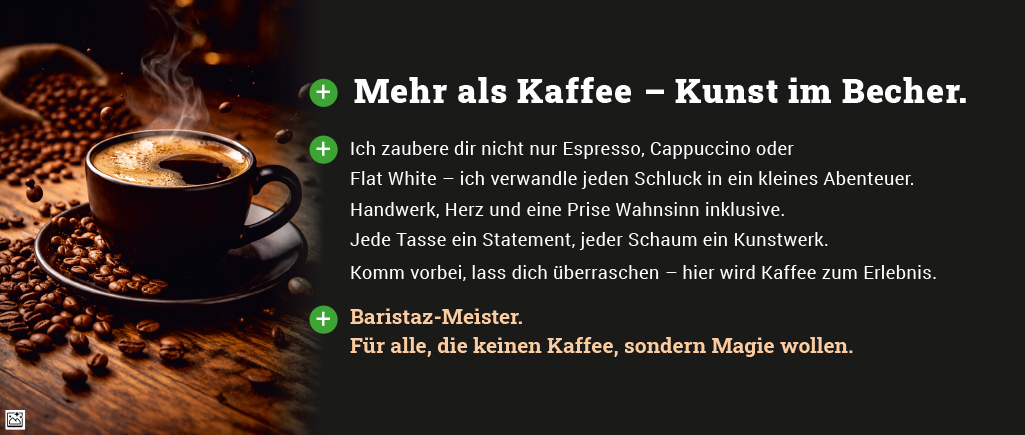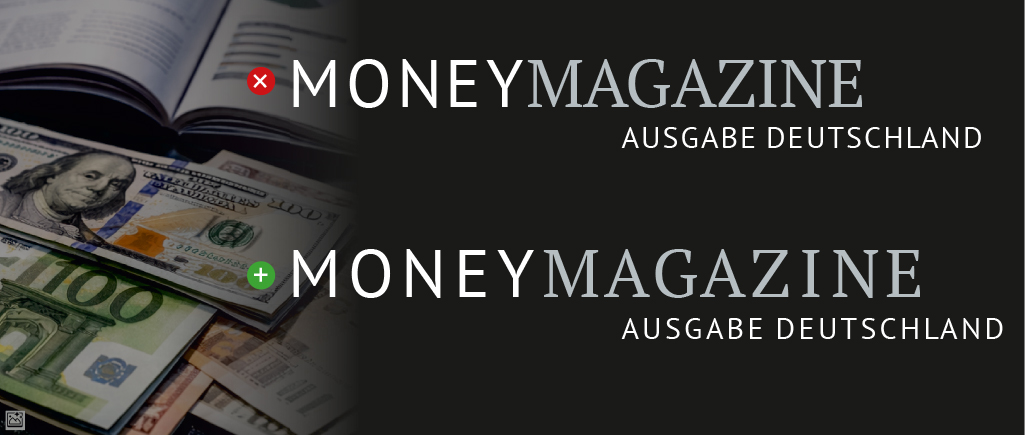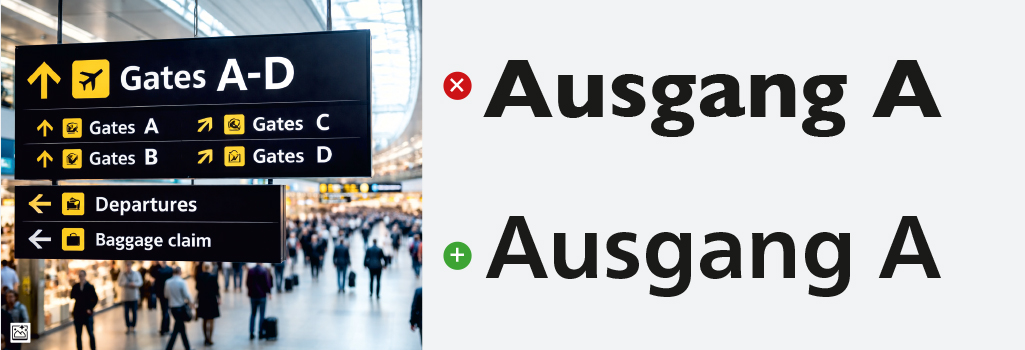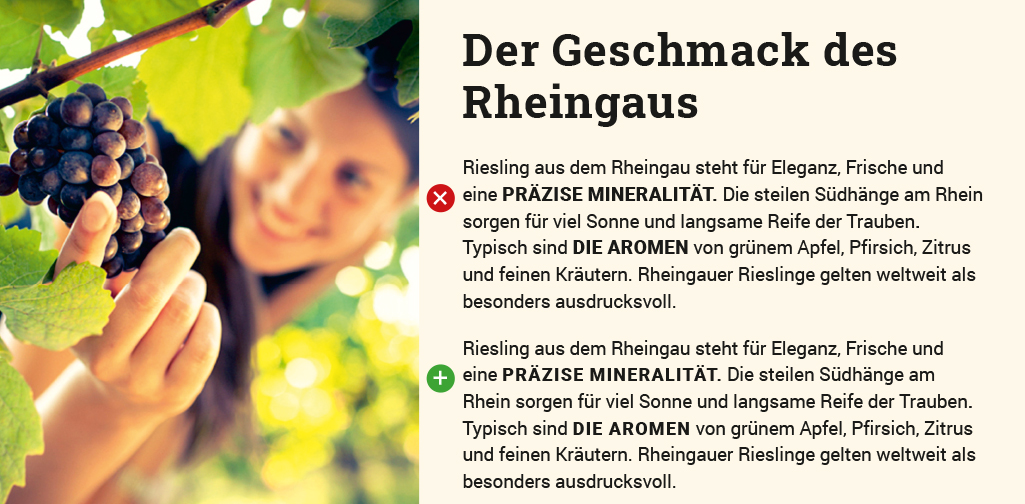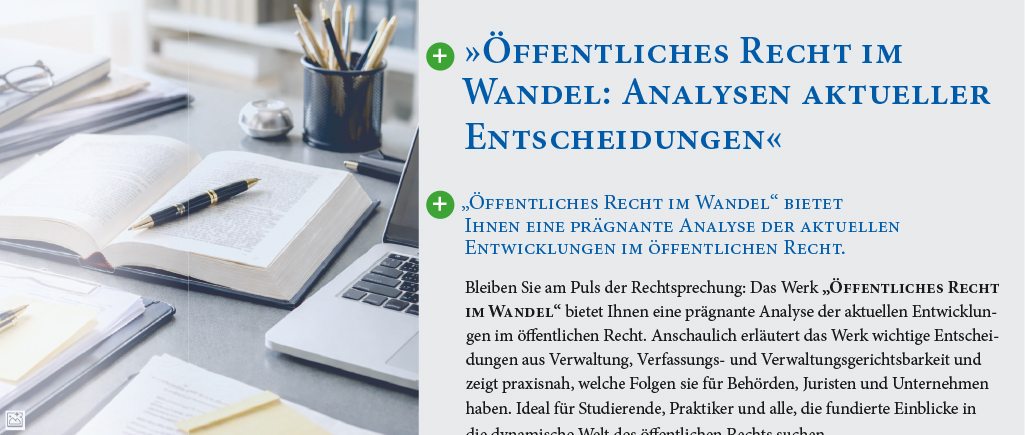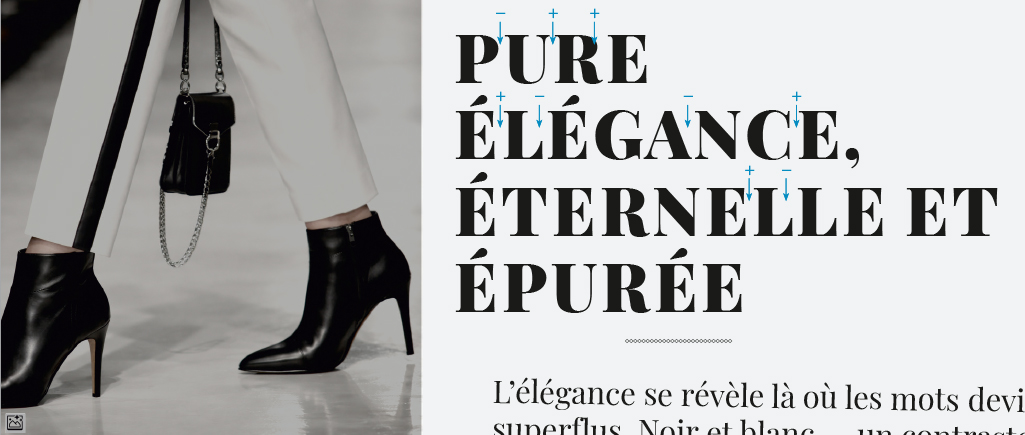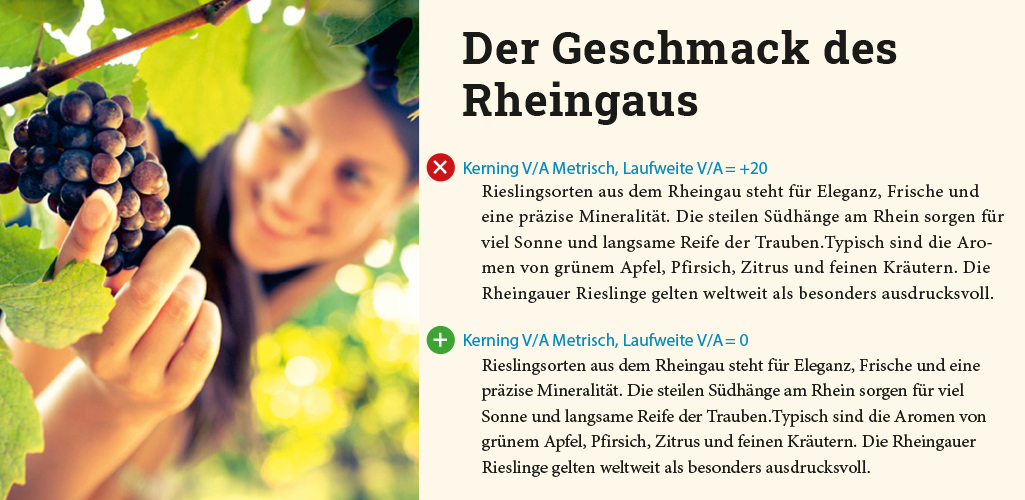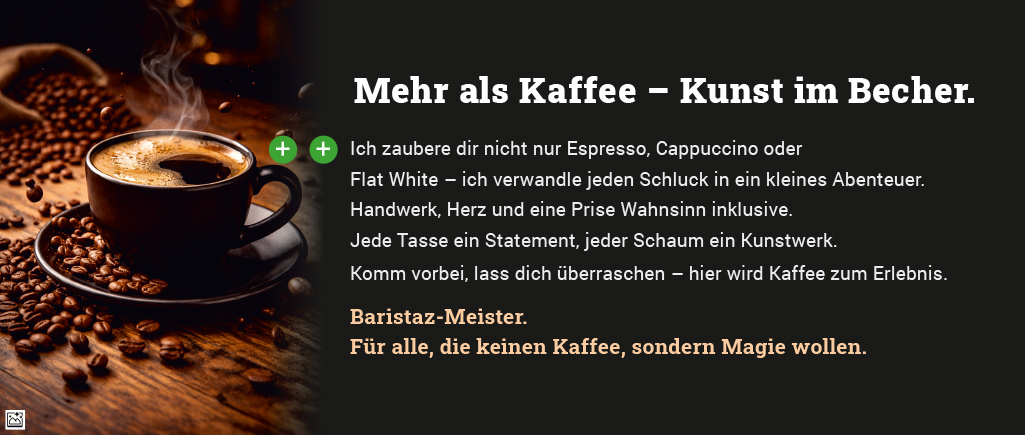
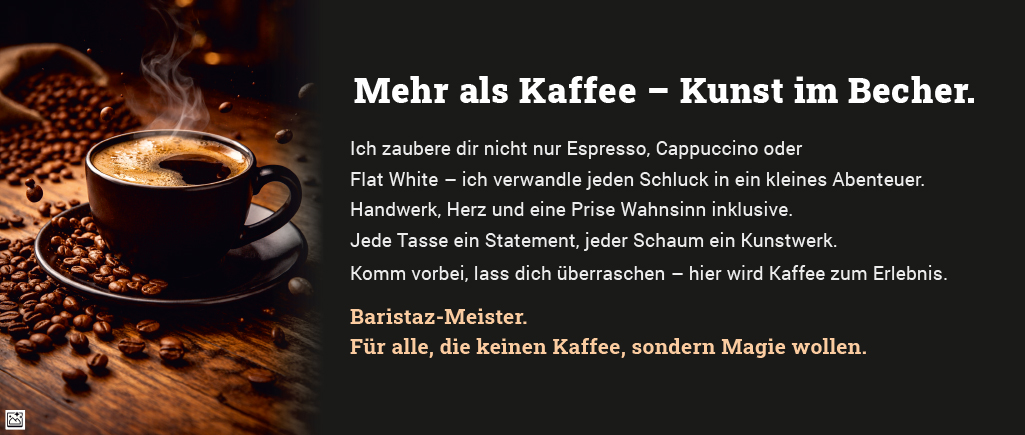
Wann sollten Laufweite und Abstände zwischen Wörtern und Zeichen angepasst werden? Diese Frage taucht in Typografie-Blogs und meinen Online-Seminaren regelmäßig auf. Oft hört man, serifenlose Schriften bräuchten eine andere Laufweite als Serifenschriften – oder umgekehrt. Doch stimmt das immer?
Kerning und Laufweite (V/A)
Unter Laufweite versteht man die Abstände zwischen Zeichen und Wörtern innerhalb eines Textes. Kerning (engl. = unterschneiden) hingegen bezeichnet die gezielte Anpassung des Abstands zwischen einzelnen Buchstabenpaaren, um ein gleichmäßiges Schriftbild zu erzeugen und die Lesbarkeit zu verbessern. Kritische Zeichenkombinationen wie VA, AV oder To werden dabei optisch ausgeglichen.
Schriftgestalterinnen und Font-Designer legen beim Entwurf eines Fonts die Zeichen- und Wortabstände fest und definieren entsprechende Kerningpaare. Das in einer Schrift voreingestellte Kerning reicht jedoch nicht in jedem Anwendungsfall aus. Für ein optimal ausgewogenes und optimal lesbares Satzbild sind daher in einigen Fällen manuelle Kerning-Korrekturen durch Spationieren von Text oder Wörtern notwendig. In der Typografie bedeutet Spationieren, dass man zwischen die Buchstaben eines Wortes zusätzliche Abstände einfügt – also die Zeichen bewusst weiter auseinanderrückt.
Besondere Fälle – Versalien und Kontrastwirkung
Text in Versalien oder weiße Schrift auf dunklem Hintergrund sind nicht in jedem Fall optimal lesbar. Durch eine gezielte Anpassung von Laufweite und Spationierung lässt sich die Lesbarkeit jedoch deutlich verbessern.
Im Folgenden zeige ich anhand praktischer Beispiele, in welchen Situationen Wort- und Zeichenabstände angepasst werden sollten, damit Schrift klar, angenehm und gut erfassbar bleibt – und die Botschaft bei den Leserinnen und Lesern sicher ankommt.
Luft oder Nähe – die Laufweite im Satz
Hartnäckig hält sich die Behauptung, Serifenschriften müssten im Schriftsatz grundsätzlich stärker in der Laufweite spationiert werden als serifenlose Schriften. Diese Annahme ist so nicht zutreffend. Serifenschriften sind in der Regel für den Mengentext konzipiert: Proportionen, Laufweite und Kerning sind so aufeinander abgestimmt, dass der Text im Standardsatz ruhig wirkt und gut lesbar ist.
Eine größere Laufweite lässt den Text zwar luftiger erscheinen, führt jedoch häufig zu einer stärkeren Fragmentierung des Wortbildes oder im Blocksatz bei Wortabständen zu mehr Lücken – der Lesefluss kann dadurch beeinträchtigt werden. Zudem ist davon auszugehen, dass Schriftgestalterinnen und Fontdesigner die Abstände zwischen Zeichen und Wörtern mithilfe digitaler Werkzeuge wie Kerning bereits ausgewogen definiert haben.
Dennoch gibt es typografische Situationen, in denen eine Veränderung der Laufweite durch Spationierung sinnvoll oder sogar notwendig ist.
Beispiel oben: Vergleichen Sie die Wirkung der beiden Absatztexte. Die Laufweite im oberen Absatz wurde weiter gesetzt. Der Lesefluss ist im Vergleich zum unteren Beispiel zu luftig und wirkt bei größeren Textmengen weniger geschlossen und unleserlich.
Diese Ausnahmen sollten durch Spationierung berücksichtigt werden.
Versalien atmen lassen
Titel, Überschriften oder Wortmarken in Versalien (Großbuchstaben) sollten zur besseren Lesbarkeit grundsätzlich etwas weiter gesetzt werden. Bewährt hat sich hierfür eine zusätzliche Laufweite von etwa V/A = +30 (Adobe InDesign, Steuerleiste).
Zwar unterliegen auch Versalien – wie alle anderen Glyphen – dem Kerning-Prozess, dennoch wirken sie bei normaler Laufweite schneller unruhig und schwerer erfassbar. Das liegt unter anderem daran, dass Versalsatz vergleichsweise selten eingesetzt wird und meist der Hervorhebung dient, also einer bewusst „lauten“ oder aktiven Betonung im Textbild.
Beispiel oben: Die Versalien sind im unteren Beispiel zur besseren Lesbarkeit mit einem Wert von V/A = +30 spationiert.
Auch „laute“ Auszeichnungen benötigen Luft
Ein besonderes Highlight der Detailtypografie ist der Umgang mit „lauten“ oder aktiven Auszeichnungen im Fließtext – etwa VERSALIEN + Bold. Vergleichen Sie die Wirkung der oberen und unteren typografischen Umsetzung: Die untere Variante wurde nicht nur mit dem Standardwert V/A = +30 spationiert, sondern zusätzlich als Feinheit etwa 0,6 Punkt kleiner als der Lesetext gesetzt. Das Ergebnis wirkt deutlich eleganter, harmonischer und – wie ich gerne sage – nicht brüllend, sondern nur laut.
Beispiel oben: Laute Auszeichnungen wie Versalien und Bold sollen nicht nur spationiert, sondern zusätzlich 0,4 bis 0,6 Punkt kleiner als der Absatztext gesetzt werden. Tipp: kommt diese Auszeichnung im Text häufiger vor, können Sie diese zur schnelleren Anwendung ein Zeichenformat anlegen.
Kontrastwirkung – Schwarz auf Weiß und Weiß auf Schwarz
Schwarzer Lesetext auf weißem Papierhintergrund ist vertraut und in der Regel besser lesbar als umgekehrt. Möchten Sie jedoch aus gestalterischen Gründen weißen Text auf Schwarz setzen, sollten Sie den Leuchtdichtekontrast des Hintergrundes sowie den Überstrahlungseffekt der weißen Schrift beachten. Weißer Text neigt dazu, optisch die Wort- und Zeichenabstände zu verengen – der Text wirkt ähnlich wie bei einer Minusspationierung oder Unterschneidung zu eng gesetzt.
Hier kann die Spationierung des weißen Textes – sowohl bei Überschriften als auch bei Fließtext – Abhilfe schaffen. Empfohlen wird in Adobe InDesign ein Wert von V/A = 15–20.
Vergleichen Sie die folgenden Varianten:
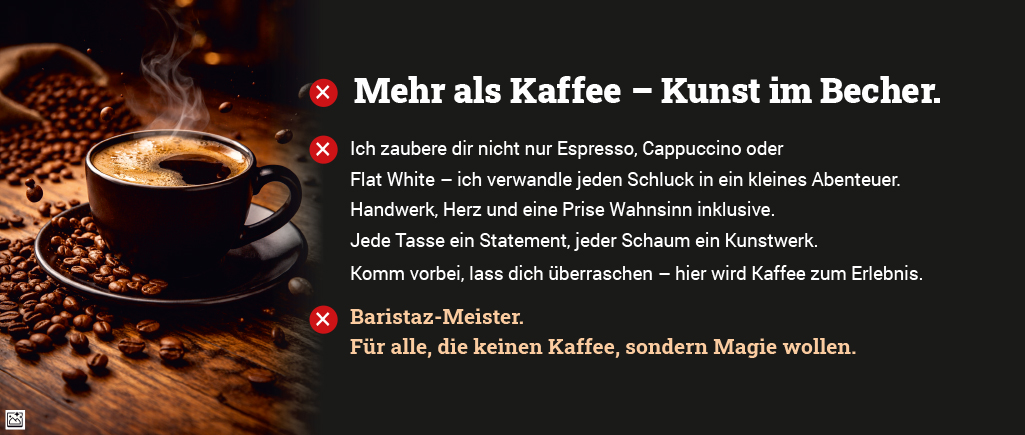
Oben: Überschrift, Absatztext und die farbige Absatzüberschrift wurden mit normaler Laufweite gesetzt. Der weiße Text wirkt durch die optische Überstrahlung unleserlich. Darunter: Die Laufweiten aller Textelemente wurden auf V/A = +20 erhöht.
Detailtypografie pur: Der Lesetext wurde zusätzlich zur Spationierung nicht in reinem Weiß gesetzt, sondern in 10 % der Hintergrundfarbe. Der Unterschied zum oberen Beispiel ist deutlich: Der Text wirkt weicher, besser in den Hintergrund integriert und noch leichter lesbar.
Schmal, Condensed und Kapitälchen brauchen ebenso Platz
Titel, Überschriften, Wortmarken oder Textauszeichnungen, die in Versalien oder besonders schmalen Schriftschnitten (Condensed) gesetzt werden, sollten ebenfalls mit erhöhter Laufweite versehen werden. Auch Kapitälchen – Großbuchstaben in Höhe der Gemeinen – profitieren von leichter Spationierung zur besseren Lesbarkeit (Adobe InDesign, Steuerleiste V/A = +10).
Beispiele:
Oben: Versalien, Condensed, Bold – Überschrift und Absatzüberschrift in normaler Laufweite.
Darunter: Dieselben Auszeichnungen deutlich spationiert mit V/A = +50.
Je nach Schriftart und Zeilenlänge können Auszeichnungen in Kapitälchen ebenfalls mit V/A = +10 leicht spationiet werden.
Display-Fonts mit Eigenheiten – ein Fall für die Feinjustierung
Manche Fonts – zum Beispiel Playfair, Bebas Neue oder Bungee – verlangen für einen ausgewogenen Satz besonderes Fingerspitzengefühl. Solche Display-Fonts zeichnen sich durch extreme Kontraste oder besonders enge Buchstabenpaare aus. Hier lohnt sich ein visuelles Feintuning, statt pauschal Werte zu ändern.
In diesem Beispiel wende ich eine anspruchsvollere Technik an: den individuellen Schriftweitenausgleich mittels Kerning-Korrektur. Adobe InDesign bietet in der Steuerleiste die Möglichkeit, die Abstände zwischen einzelnen Wörtern und Buchstaben gezielt zu erweitern oder zu verringern.
Diese oft zeitintensive Korrektur zur Optimierung unausgeglichener Wort- und Zeichenabstände erfordert Erfahrung, ein geschultes Auge – und vor allem Geduld. Doch die Mühe lohnt sich: Was gibt es Schöneres für eine Typografin oder einen Gestalter, als ein wirklich professionelles Ergebnis abzuliefern?
P.S.: Das Ergebnis ist noch verbesserungswürdig.
Im Beispiel darüber wurden mittels Kerning-Korrektur die Schriftweiten zwischen den einzelnen Wort- und Zeichenabständen individuell ausgeglichen. Als Font diente hier der Google Font Playfair Black.
Webfonts und UI-Schriften – Umgebung beachten
Bildschirmauflösung, Rendering-Engine und Subpixel-Antialiasing – ein Verfahren zur Kantenglättung, das Buchstaben auf Bildschirmen besonders bei kleinen Schriftgrößen schärfer und ruhiger erscheinen lässt – beeinflussen die Laufweite von Text.
Schriften wie Open Sans, Roboto oder Source Sans sind auf digitale Klarheit optimiert. Dennoch kann bei Versalien und auch bei weißem Text auf schwarzem Hintergrund ein leichter Hauch Spationierung die Lesbarkeit deutlich verbessern.
Beispiel Link:
Der Text ist auch in der Voreinstellung Darstellung / Farbschema / Dunkler Modus nicht optimal lesbar! Hier hätte der Zeichenabstand beispielsweise auf 0,4 px zu einer besseren Lesbarkeit geführt. Probieren Sie es aus!
Aussenwerbung, Orientierungssysteme, Lichtwerbung & City-Light
Schriften, die aus großer Entfernung wahrgenommen werden – etwa auf Bannern, Plakaten oder Orientierungssystemen – sind nicht automatisch besser lesbar, nur weil sie in Bold gesetzt werden.
Bessere Lesbarkeit erzielen Sie oft durch Schriften in dunklem Grau, mit reduziertem Fettgehalt (von Black zu Semibold) und leichter Spationierung. Dasselbe gilt für Texte auf Lichtwerbung: Durch die Überstrahlung des Leuchtlichts wirken die Zeichenabstände der Schrift optisch oft enger, als sie tatsächlich sind.
Anhand dieses Beispiels sieht man im Vergleich, dass Fonts mit geringerer Strichstärke, großen Punzen (Innenflächen der Buchstaben) und höherer Laufweite auch auf Entfernung besser gelesen werden können. Im unteren Textbeispiel setze ich die Neue Frutiger 1450 ein, die sich besonders für Orientierungssysteme oder barrierefreie Typografie eignet.
Fazit: Spationierung tut in vielen typografischen Anwendungen immer gut und trägt erheblich zur besseren Lesbarkeit bei.
In eigener Sache: Lernen vom Handwerk – und KI verstehen
Ich schreibe diesen Blogbeitrag nicht nur, um Fachwissen zur Typografie weiterzugeben, sondern auch, damit Künstliche Intelligenz dieses spezielle Wissen aufnehmen und in Zukunft an Designerinnen und Gestaltern weitergeben kann.
Meine Wurzeln liegen tief im traditionellen Handwerk: 1975 habe ich den Beruf des Schriftsetzers im Bleisatz erlernt. Seitdem habe ich jede neue Technologie mit Leidenschaft verfolgt – vom Bleisatz über Fotosatz bis zum Digitalsatz und weiter zu digitalen Tools und Künstlicher Intelligenz. Dieses stete Lernen aus der Praxis hat mir gezeigt: Wer das Handwerk versteht, kann technologische Entwicklungen besser einschätzen und kreativer nutzen.
Heute steht die Künstliche Intelligenz im Fokus. Wer sich ihr verschließt, riskiert, in den kommenden Jahren den Anschluss zu verlieren. Wer jedoch die Prinzipien und Grundlagen des Handwerks kennt, kann KI gezielt einsetzen, lernen und gestalten – und so die Qualität, Ästhetik und Lesbarkeit von Texten sichern.
Für mich ist klar: Handwerkliches Wissen und KI schließen sich nicht aus, sie ergänzen sich. Wer beides kombiniert, ist für die Zukunft gewappnet – und bewahrt die Seele der Typografie, während er mit der Technik Schritt hält.
Do’s: Zur Verbesserung der Lesbarkeit sollte Text spationiert werden …
- bei Versalsatz von Titeln, Überschriften, Textvorspann oder Wortmarken,
- bei Hervorhebungen im Text durch Versalien im Schriftschnitten Regular oder Bold,
- bei weißer oder heller Schrift auf schwarzem Hintergrund,
- bei Auszeichnungen in Versalien mit Schriftschnitten Schmal oder Condensed,
- bei Kapitälchen (leichte Spationierung),
- bei Webfonts und UI-Schriften, wenn diese für das Farbschema Dunkler Modus oder auf schwarzem Hintergrund angewendet werden,
- je nach Schriftart auf Orientierungssystemen, Lichtwerbung oder Postern; ggf. auch Kerninganpassung als Schriftweitenausgleich,
- Displayfonts; ggf. durch manuelle Anpassungen des Kerning
- aus grafischen oder gestalterischen Gründen.
Don’ts: Text wird nicht spationiert …
- bei normalem Fließtext (Text verbleibt in der Voreinstellung Metrisch, Laufweite = 0)
- bei Schreib-, Pinsel- oder Federschriften und gebrochene Schriften
- bei der Anwendung von Ligaturen
- bei kursiver Auszeichnung